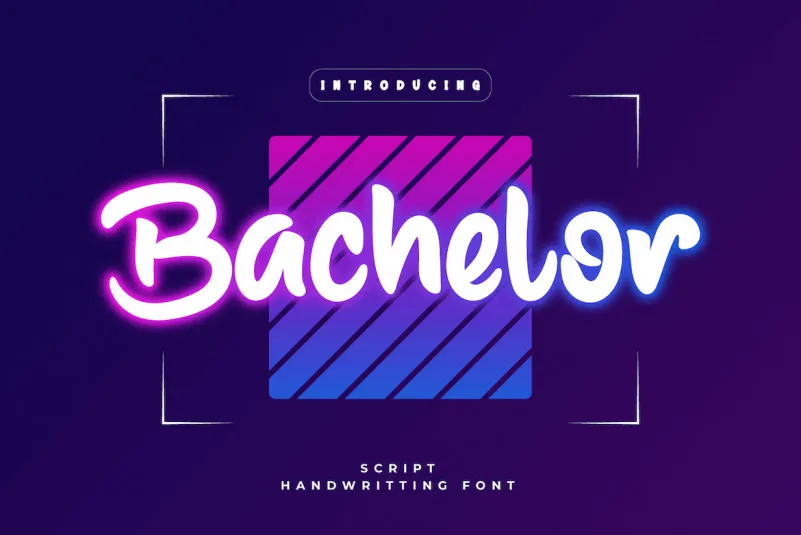
Bachelor Font – Download Grátis
Aqui está uma versão em português do Brasil de 2 parágrafos curtos para a descrição da fonte ‘Bachelor Font’: Esta é uma fonte projetada com um toque suave e delicado, mas também elegante e refinado. Com seu design cuidadosamente elaborado, esta fonte se destaca perfeitamente para textos e cabeçalhos em projetos especiais de design. Ideal para aquelas criações que exigem um toque sofisticado ou uma aparição única, a ‘Bachelor Font’ oferece uma opção moderna e versátil para personalizar textos em sites, redes sociais, livros impressos ou qualquer outro projeto onde o texto adquire importância. Com seu charme pessoal e sua aparência impecável, essa fonte é um excelente complemento para quem valoriza a qualidade e a elegância no design de fontes.
Designer: productype